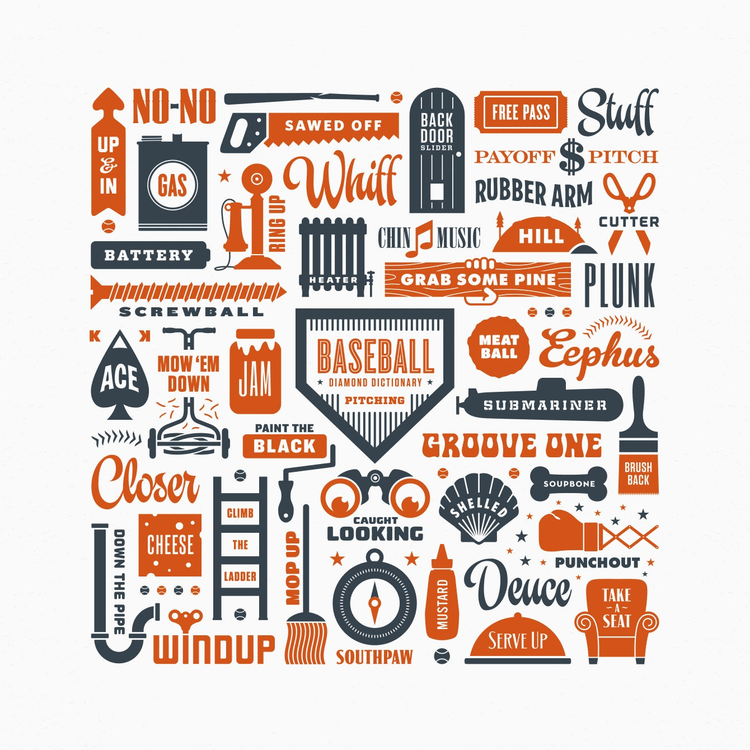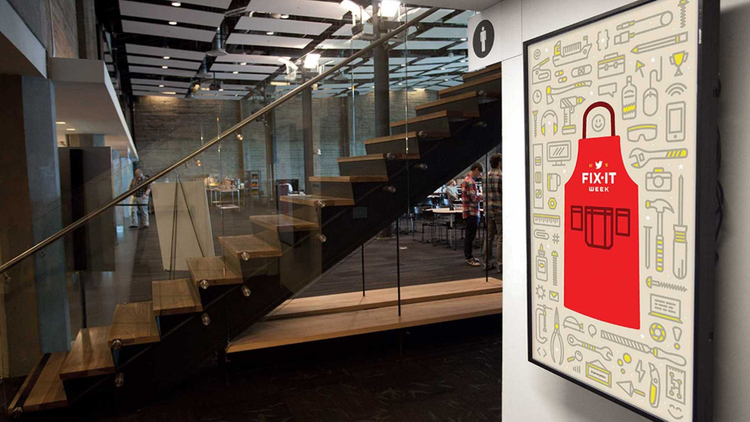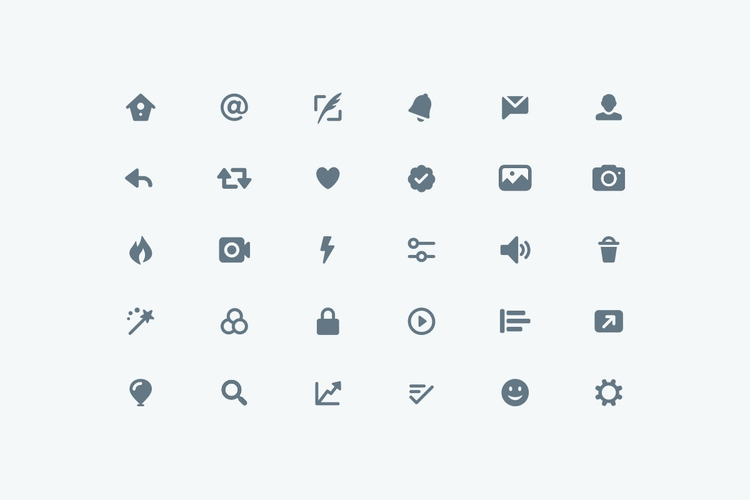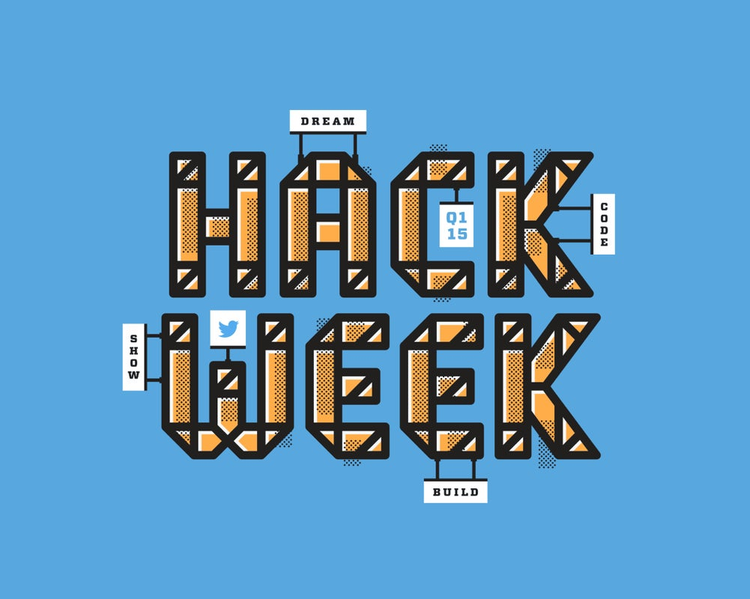
Ikonografie, Typografie und Twitter: Jeremy Reiss über den Charakter von Produkten
Design und Baseball, das sind die beiden Leidenschaften von Jeremy Reiss. Durch die Kombination aus beiden landet er schließlich einen Homerun. Jeremy Reiss twittert viel. Aber dass Twitter wegen einer seiner Arbeiten – einer Illustration zum Thema Baseball mit eigener Typografie – mal bei ihm anklopfen würde, hätte er nicht gedacht.
Jetzt ist er Teil des Twitter-Teams für Produkt-Design, wo er sein Wissen über Typografie und Ikonografie bei der subtilen Neugestaltung der App einbringen kann. Wir haben ihn gebeten, uns seine Arbeit zu zeigen und uns ein paar Tipps zu geben, wie Designer mithilfe von Typografie und Ikonografie ihren Werken Charakter verleihen können.
Wie können Designer ihren Apps oder Websites Charakter verleihen?
Zuallererst muss ein Designer gemeinsam mit seinen Kunden (den Entscheidern) herausfinden, was diese unter „Charakter“ verstehen. Wenn das klar ist, ist meiner Meinung nach eine auf das Unternehmen abgestimmte Kombination aus Farbe, Typografie und eingängigen visuellen Elementen der Schlüssel zu Design mit Charakter.
Wie machst du das für Twitter?
Als ich gebeten wurde, die Twitter-Icons zu überarbeiten, war schnell klar, dass ich zwei Dinge tun musste: die Icons stilistisch vereinheitlichen und ein Design finden, das Twitter einen persönlicheren Touch verleiht.
Die einheitliche Optik haben wir erreicht, indem wir bei allen Icons die gleiche Konturstärke verwendet haben. Um die Icons einladender und weniger streng wirken zu lassen, haben wir alle Ecken abgerundet.
Warum spielen Typografie und Ikonografie im Design des 21. Jahrhunderts eine so große Rolle?
Typografie transportiert sehr schnell einen gewissen Charakter. Mit einem Blick kommt rüber, ob Inhalte verspielt oder seriös, unterhaltsam oder nüchtern, abgehoben oder nahbar sind. Egal ob es um individuelle oder selbst gezeichnete Typen oder um Schriften von professionellen Anbietern geht – sie alle haben ihre eigene Charakteristik.
Spätestens seitdem wir alle ein Mobilgerät mit uns herumtragen, wollen wir auch nicht lange auf Antworten warten. Hier kommt die Ikonografie ins Spiel, denn Icons sind die Bildsprache, die uns schnell zu den gesuchten Antworten führen.
Wie bist du im Bereich Design ausgerechnet auf Schriften, Symbole und Grafiken gekommen?
Ich fand schon als kleiner Junge die Schilder für den Garagenflohmarkt toll, die mein Vater damals gemalt hat. Sie waren nur aus einfacher weißer Pappe, aber mit seinen schön herausgearbeiteten, handgemalten Buchstaben und den Farben machte mein Vater daraus echte Hingucker, die die Leute angelockt haben. Ich habe seitdem nie wieder so schöne Schilder für einen Garagenflohmarkt gesehen. Das war, glaube ich, der Auslöser für meine Leidenschaft für Design.
Welchen Herausforderungen müssen Designer sich heute stellen?
Bei Illustrationen wird es immer schwieriger, sich stilistisch von anderen abzuheben und sich einen Namen zu machen. Es gibt so viele Plattformen, auf denen Designer ihre Arbeiten veröffentlichen und sich Inspiration holen können. Bei all diesen tollen Arbeiten ist es aber auch umso schwieriger, bemerkt zu werden.
Da es Apps und Webstandards nun schon eine Weile gibt, gibt es für die meisten Projekte Richtlinien und Vorlagen. Also liegt die Herausforderung darin, im Rahmen der Vorgaben mit originellen, frischen Ideen aufzuwarten.
In welche Richtung entwickelt sich Design?
Alles läuft darauf hinaus – oder ist womöglich schon so – dass junge Designer in sehr frühen Phasen ihrer Karriere immer ausgefeiltere Designs entwickeln. Die moderne Technologie hat hier die Tür zu schnelleren Lernprozessen geöffnet.